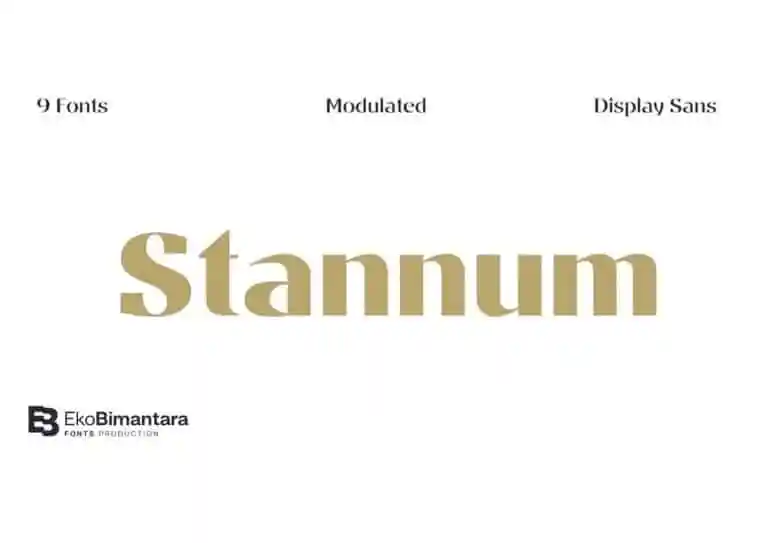
Stannum Sans Serif Font
A fonte Stannum Sans Serif é uma escolha perfeita para projetos que buscam simplicidade e elegância. Conhecida por sua versão sem serif, essa fonte oferece um toque de modernidade aos textos, tornando-a ideal para aplicações digitais como headlines ou marcas de marca. Desenvolvida pelo designer Eko Bimantara, ela se destaca especialmente quando usada em conjunto com letras maiúsculas e minúsculas e linguagens multilíngues. Com um total de 380 grafos para suportar uma ampla gama de idiomas latinos, a Stannum Sans Serif é ideal tanto para uso visível quanto para escritas curtas em páginas web. Suavemente compacta, essa família de fontes conta com sete pesos distintos que vão do fino ao grosso, criando um amplo espectro de opções estilísticas e funcionalidades. Ideal para aplicativos de mídia visual, nomes de marcas e headlines, a Stannum Sans Serif oferece uma variedade de possibilidades que se adaptam perfeitamente às necessidades digitais modernas.